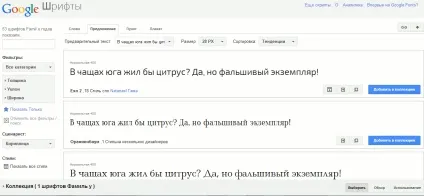
Шрифти для сайту в css
Привіт шановні початківці веб майстра.
У цій статті ми дізнаємося, які шрифти застосовуються в інтернеті, і як вони оформлюються властивостями CSS.
Які з них однаково відображаються у всіх браузерах, і операційних системах, і які потрібно впроваджувати через сервіс, що забезпечує це коректне відображення.
І звичайно ж подивимося, як впровадити вільний шрифт на сайт управляється CMS WordPress.
Шрифтів в інтернеті величезна кількість, і всі вони об'єднаних в декілька сімейств. Щоб розглянути їх усі, напевно буде потрібно ще один такий сайт, як мій.
Проблема в тому, що є таке явище, як кроссбраузерность, тобто можливість будь-якого елементу, однаково відображатися у всіх наявних в інтернеті браузерах.
І не тільки в браузерах. Для шрифтів в це поняття входять всі операційні системи. Тому гарантувати, що будь-якої шрифт відобразитися однаково абсолютно на всіх екранах моніторів, неможливо.
Щоб уникнути явних відмінностей при відображенні шрифту, разом з назвою, зазвичай вказується сімейство, в яке він входить.
І якщо будь-якої браузер або операційна система його не зрозуміють, то в 99% випадків, вони покажуть шрифт з того ж сімейства, що не особливо зіпсує дизайн сторінки.
Звичайно, такий стан зі шрифтами не можна назвати нормальним, і воно не залишилося без уваги розумних хлопців з команди Google.
Ними був створений сервіс «Google Fonts», який змінив ситуацію в кращу сторону, але про нього в кінці статті.
А поки я представлю список тих шрифтів, які входять в найбільш поширені ОС, а значить в більшості випадків відобразяться так як положено.
1. Сімейство sans-serif - шрифти без зарубок, з прямими чітко прописаними контурами.
Тепер подивимося, як задаються шрифти в таблицях стилів. Спочатку вибирається селектор, в області якого ми збираємося поставити певний шрифт.
Це може бути тег
, якщо ми захочемо поставити шрифт для всієї сторінки, можуть бути теги, якщо шрифти будуть задаватися для заголовків або абзаців.
Задаються шрифти за допомогою властивості CSS font-family. а в значенні вказується назва шрифту.
Як я вже говорив, після назви шрифту, через пробіл, вказується сімейство шрифту.
Робиться це для того, щоб якщо будь-якої з браузерів відвідувачів Вашого сайту не зможе відобразити саме той шрифт, яким написано Ваш сайт, він відобразить шрифт з того ж сімейства.
І ще одне правило. Якщо назва шрифту складається з декількох слів, то при написанні в стилі, його потрібно брати в лапки, якщо слово одне - без лапок.
Спробуйте різні шрифти, і в майбутньому будете знати, який з них використовувати для свого сайту.
Розмір і колір шрифту
Розглянемо, як в CSS задається розмір і колір шрифту. Розмір шрифту задається в пікселях (px), рідше у відсотках (%), і зовсім рідко в одиницях (em) і пунктах (pt).
Базовий розмір шрифту становить: 16px, 100%, 1em, 12pt. Значить, якщо нам буде потрібно збільшити, або зменшити шрифт, ми будемо рухатися від цих даних в бік збільшення, або зменшення.
Властивість для завдання розміру шрифту називається font-size. і давайте встановимо його для всіх абзаців, припустимо, в 18px.
Так само можна задати це властивість заголовку h1. в тому випадку, якщо розмір заголовка потрібно ще збільшити
Колір шрифту задається властивістю color
Можна так само задати розмір і колір якогось слова чи речення розташованому всередині абзацу, використовуючи тег і атрибут style
тег вводить в html код вбудовані стилі. Трохи нижче розглянемо, як те ж саме робиться за допомогою класів.
Тепер подивимося, як відобразить цей код браузер.
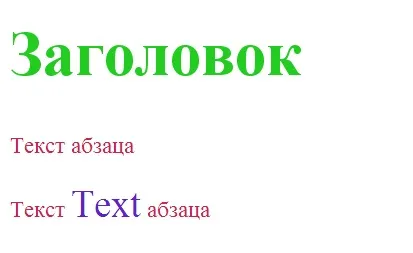
Ось так засобами css, можна маніпулювати розміром шрифту. Точно так само можна задати розмір у всіх інших одиницях вимірювань, але ми не будемо на цьому зупинятися детально.
Головне їх знати, щоб в подальшому, якщо доведеться працювати з будь-яким кодом, мати уявлення, що за значення вказано у властивості font-size.
Жирний і курсивний шрифт
Товщина шрифту задається властивістю font-wieght. яке набуває таких значень:
1. normal - нормальний;
2. bold - напівжирний;
3. bolder - жирніше батька;
4. lighter - тонше батька;
5. від 100 до 900 - цифрове значення, не володіє кросбраузерністю;
Курсив задається властивістю font-style. приймають значення - italic.
Щоб мати можливість виділяти жирним або курсивом різні ділянки тексту, потрібно створити селектори класів c цими властивостями, і за допомогою тега вставляти їх в потрібні місця.
Розтягнутий і стислий шрифт
У шрифту можна змінити відстань між символами і словами.
Для зміни відстані між символами застосовується властивість css letter-spacing
Для зміни відстані між словами застосовується властивість word-spacing
Обидва ці властивості приймають і негативні значення, тобто зі знаком мінус, дія яких зменшує відстані задані шрифту за замовчуванням.
додаткові шрифти
А тепер, як і було обіцяно, познайомимося, і навчимося користуватися сервісом Google Fonts
Якщо Ви захочете виділити даними шрифтом частина тексту, або будь-яке слово в статті, то цей текст або слово потрібно укласти в наступний код:
Якщо ж Вам захочеться всю статтю відобразити таким шрифтом, то немає проблем. Укладайте в це код весь наявний текст.